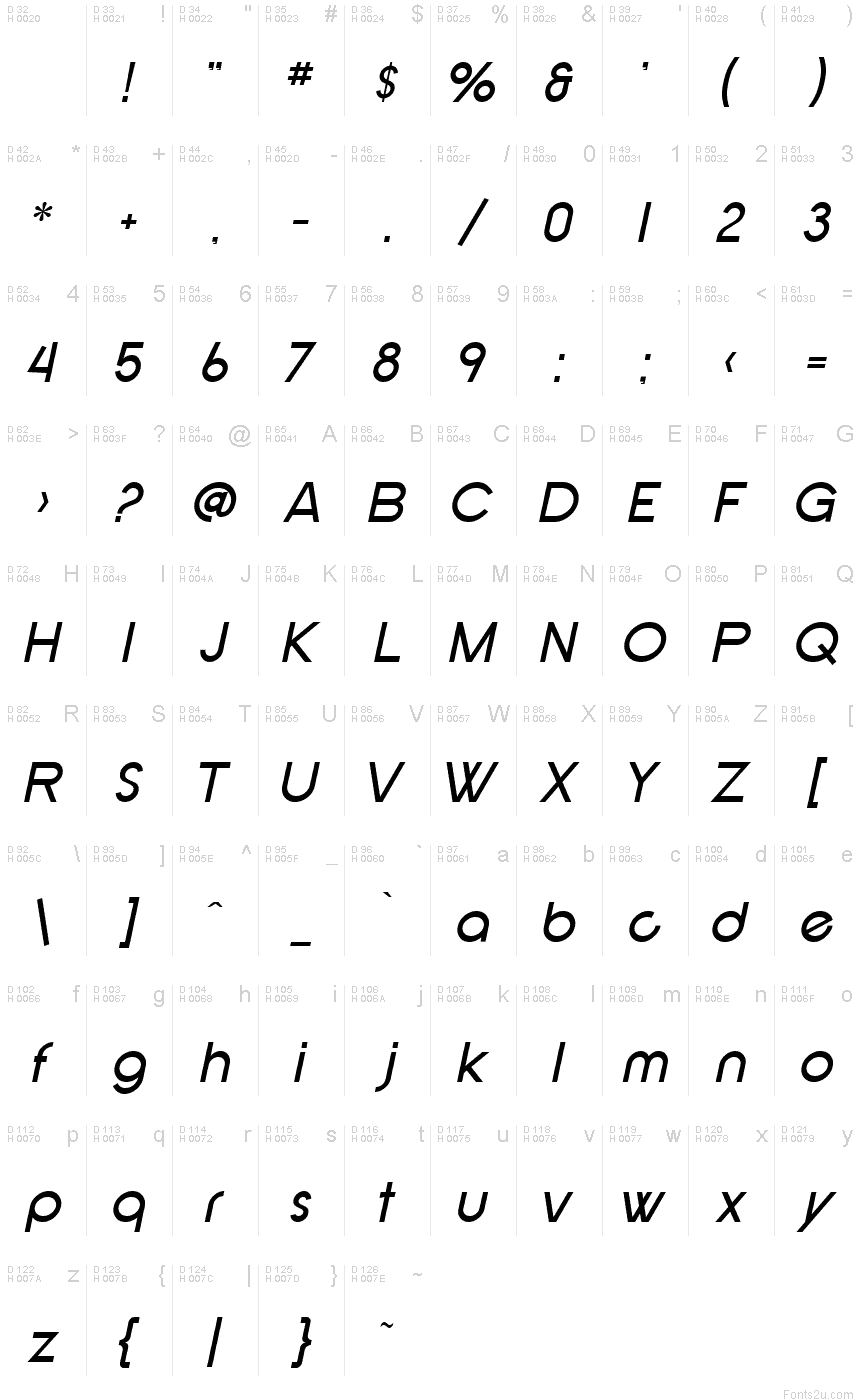
SF New Republic Italic od ShyFoundry to bezpłatny, pochyły krój bezszeryfowy o żywym, wczesnomodernistycznym charakterze. Litery są mocno pochylone i minimalistyczne, a połączenie szerokich, otwartych łuków z ostrymi skosami nadaje całości szybki, czysty i nieco filmowy wygląd, daleki od nudnej neutralności.
Świetnie sprawdzi się na plakatach, okładkach magazynów, w napisach tytułowych, brandingu i okładkach albumów, gdzie potrzebny jest darmowy font pełen dynamiki, ale nieprzesadzony. Mocne pochylenie i oszczędna forma dobrze wyglądają też w krótkich nagłówkach i logotypach, szczególnie gdy zależy Ci na wyrazistym, miejskim stylu z nutą retro, która nie wpada w nostalgię.
SF New Republic